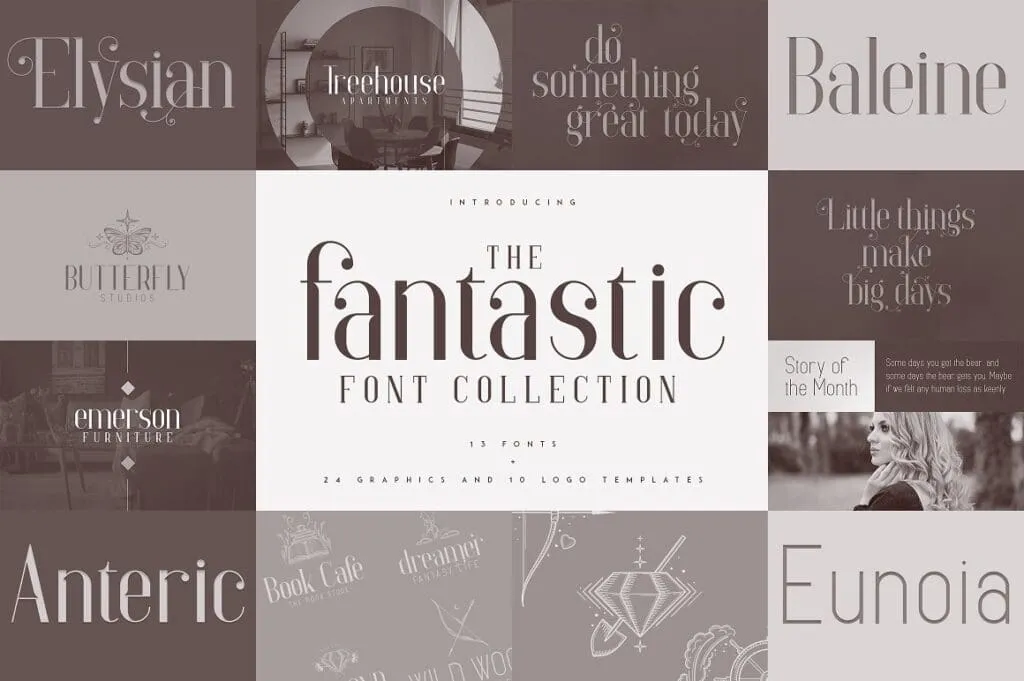
مجموعة رائعة – خطوط والشعارات Fantastic Collection – fonts & logos 5914443
حول المنتج
تقديم مجموعة رائعة – الخطوط والشعارات
The Fantastic Font Collection عبارة عن حزمة عتيقة وغير رسمية محملة بـ 13 خطًا ورسومات وقوالب شعارات. إنها خطوط متعددة الاستخدامات تعمل بشكل رائع في الأحجام الكبيرة والصغيرة.
هذه المجموعة مثالية لمشاريع العلامات التجارية ، وتصميمات الأدوات المنزلية ، وتغليف المنتجات ، ورؤوس المجلات – أو ببساطة كتراكب نص أنيق لأي صورة خلفية.
ستجد في هذه المجموعة:
خط اليزيان سيريف
الأربطة
مناوبين
دعم متعدد اللغات
محرف Eunoia
4 أوزان
الأربطة
دعم متعدد اللغات
نص إليسيان
الأربطة
مناوبين
دعم متعدد اللغات
محرف باليني سيريف
4 أوزان
الأربطة
دعم متعدد اللغات
محرف أمامي
3 أوزان
الأربطة
دعم متعدد اللغات